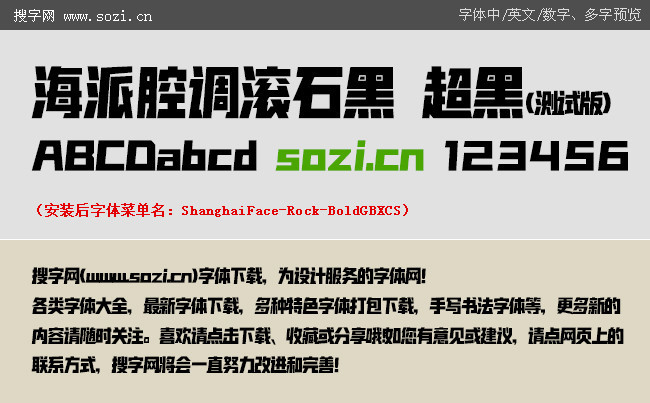
海派腔調(diào)滾石黑-超黑(測試版)
搜字網(wǎng)提供一款海派腔調(diào)滾石黑-超黑(測試版)中文字體下載海派腔調(diào)滾石黑是一款十分漂亮的藝術(shù)字體,字體略微傾斜,清晰、醒目,整體美觀大氣,適合用于報刊標頭設(shè)計,包裝設(shè)計,海報設(shè)計等廣告應(yīng)用。(此款為個人非商用版,如需商用請聯(lián)系銳字工房購買)